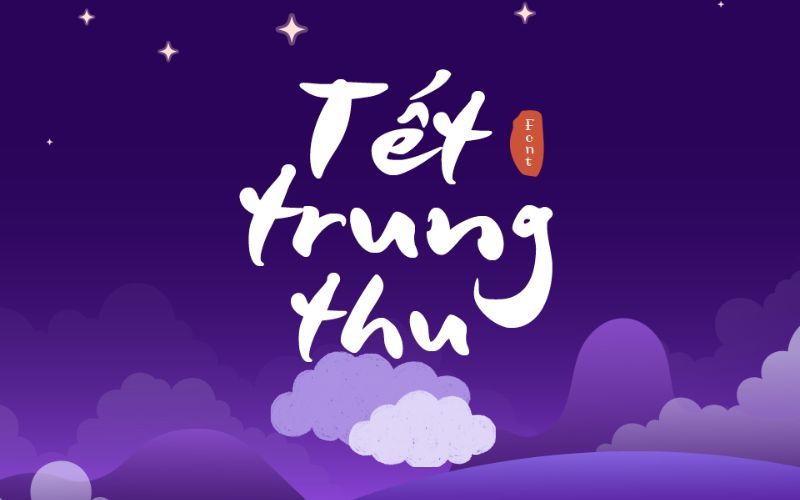
Trong thiết kế truyện tranh hay các sản phẩm sáng tạo như poster, video hoạt hình, font chữ đóng vai trò quan trọng trong việc thể hiện cảm xúc và phong cách riêng. Nếu bạn muốn mang đến sự sinh động, hài hước và cá tính cho tác phẩm, thì tải font chữ truyện tranh chính là lựa chọn hoàn hảo. Những bộ font chữ truyện tranh Việt hóa không chỉ giúp đoạn hội thoại trở nên tự nhiên, dễ đọc mà còn tăng tính thẩm mỹ cho toàn bộ thiết kế. Cùng Vietkey khám phá ngay các font truyện tranh đẹp và cách tải nhanh chóng trong bài viết dưới đây.
Giới thiệu chung về font chữ truyện tranh
Font chữ truyện tranh là kiểu chữ được thiết kế riêng để thể hiện cảm xúc, hành động và lời thoại trong các tác phẩm manga, comic hay truyện tranh minh họa. Khác với font chữ thông thường, font truyện tranh có đường nét sinh động, mềm mại hoặc phá cách, giúp người đọc cảm nhận được cảm xúc nhân vật một cách trực quan hơn.
Không chỉ giới hạn trong truyện tranh, những font chữ truyện tranh Việt hóa ngày nay còn được ứng dụng rộng rãi trong thiết kế poster, banner, video hoạt hình, hay các ấn phẩm sáng tạo dành cho trẻ em. Nhờ sự đa dạng về phong cách – từ dễ thương, vui nhộn đến mạnh mẽ, hành động – các font này giúp nhà thiết kế tự do thể hiện cá tính và phong cách riêng trong từng dự án.
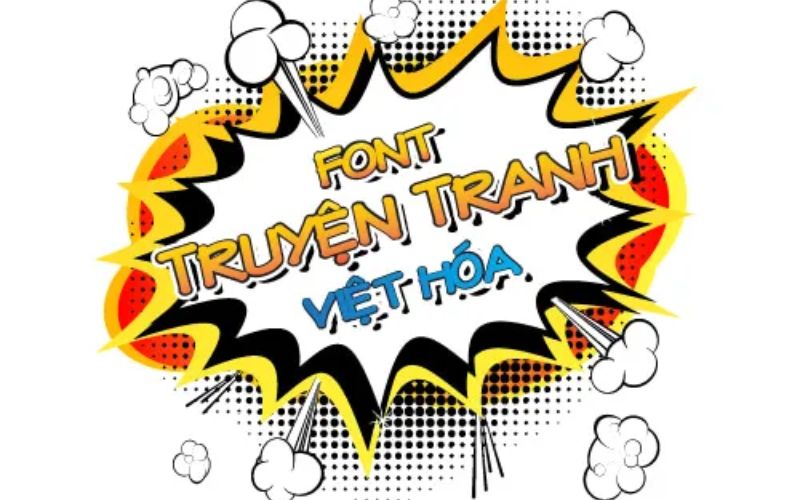
Vì sao nên dùng font chữ truyện tranh?
Việc sử dụng font chữ truyện tranh không chỉ giúp tác phẩm trở nên sinh động hơn mà còn góp phần truyền tải cảm xúc và câu chuyện một cách rõ nét hơn. Mỗi kiểu font đều mang một sắc thái riêng — có loại tươi vui, dễ thương phù hợp với truyện thiếu nhi, có loại mạnh mẽ, góc cạnh dành cho truyện hành động hay phiêu lưu.
Ngoài ra, font truyện tranh Việt hóa còn giúp người sáng tạo dễ dàng Việt hóa nội dung mà vẫn giữ được phong cách đặc trưng của truyện tranh Nhật Bản hay Âu Mỹ. Với các nhà thiết kế, việc chọn đúng font sẽ giúp bố cục hài hòa, thu hút ánh nhìn và tạo dấu ấn riêng cho sản phẩm. Vì thế, sử dụng font truyện tranh là yếu tố không thể thiếu để nâng cao chất lượng hình ảnh và trải nghiệm thị giác của người đọc.
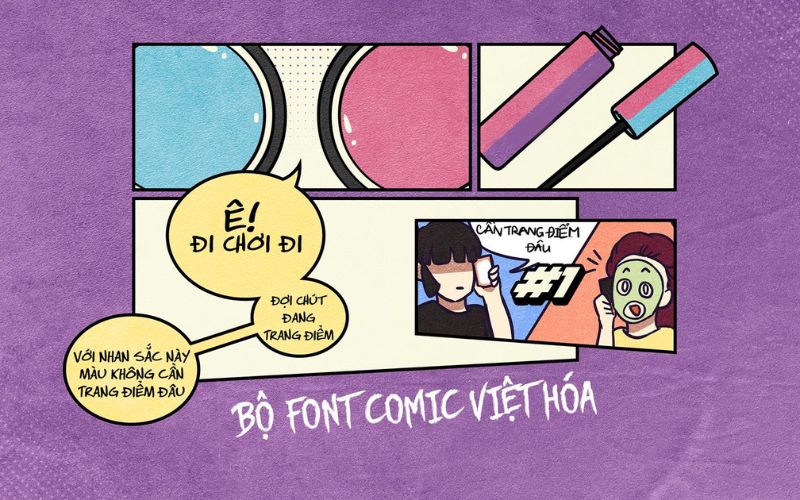
Các font chữ truyện tranh đẹp và dễ dùng nhất hiện nay
Nếu bạn đang tìm kiếm những kiểu chữ sinh động, đậm chất comic để làm nổi bật tác phẩm của mình, thì các font chữ truyện tranh đẹp và dễ dùng nhất hiện nay dưới đây chắc chắn sẽ là lựa chọn hoàn hảo.
Font Teddy Bear
Font Teddy Bear mang phong cách ngộ nghĩnh, đáng yêu, thường được sử dụng trong truyện tranh dành cho thiếu nhi hoặc các thiết kế vui nhộn. Các nét chữ tròn trịa, mềm mại tạo cảm giác thân thiện và dễ đọc. Khi tải font chữ truyện tranh Teddy Bear, bạn có thể áp dụng cho tiêu đề truyện, tranh minh họa hoặc poster hoạt hình. Đây là lựa chọn hoàn hảo cho những ai muốn mang lại cảm xúc nhẹ nhàng, vui tươi trong thiết kế mà vẫn giữ được sự chuyên nghiệp và thẩm mỹ cao.
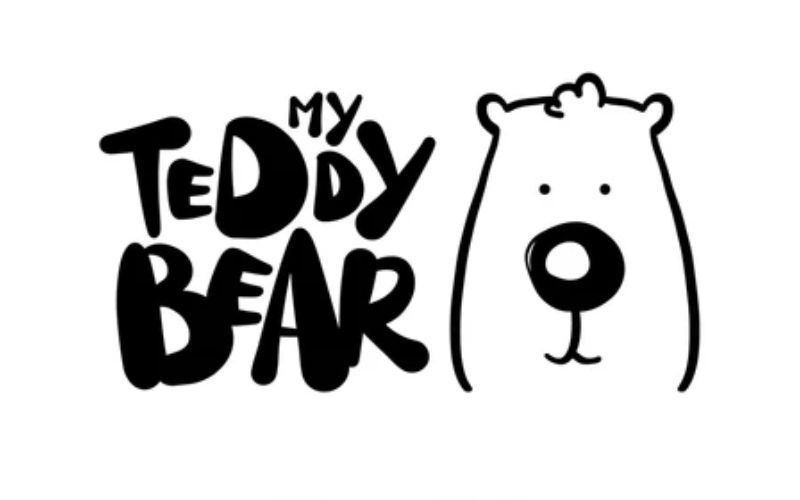
Font Anime Ace 3 Việt hóa
Anime Ace 3 Việt hóa là một trong những font truyện tranh phổ biến nhất hiện nay, đặc biệt được ưa chuộng trong các bản truyện Việt hóa. Font có thiết kế rõ ràng, đậm nét và phù hợp cho phần thoại, lời kể hoặc hiệu ứng âm thanh trong manga. Khi tải font chữ truyện tranh Anime Ace 3 Việt hóa, bạn sẽ có được kiểu chữ mang phong cách Nhật Bản đặc trưng, vừa hiện đại vừa dễ đọc. Đây là lựa chọn lý tưởng cho các nhóm dịch truyện, họa sĩ hoặc nhà thiết kế yêu thích phong cách comic – anime.
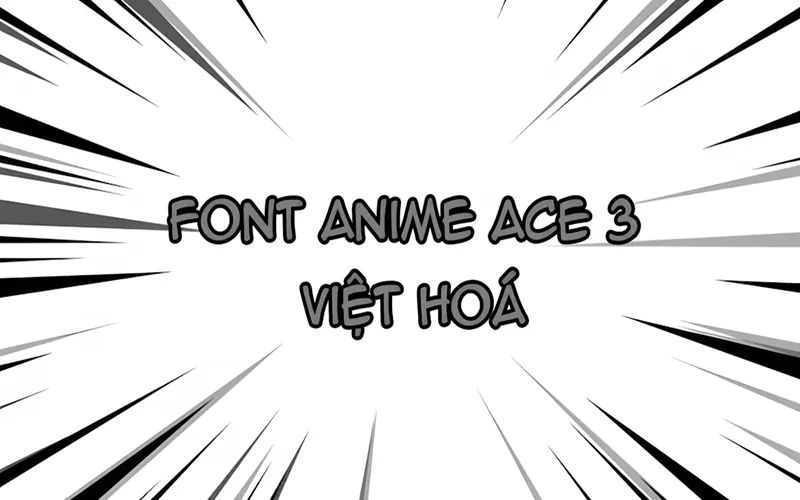
Font HL Comic
Font HL Comic nổi bật với kiểu chữ dày, chắc và có độ tương phản cao giữa các nét, mang lại cảm giác mạnh mẽ và sinh động. Font này thường được sử dụng trong truyện tranh hành động hoặc các thiết kế cần sự nổi bật về thị giác. Khi tải font chữ truyện tranh HL Comic, bạn có thể dùng để thiết kế tiêu đề, hiệu ứng “boom”, “bang” hoặc lời thoại nhân vật. Với khả năng hiển thị tốt cả trên màn hình và in ấn, HL Comic là lựa chọn hoàn hảo cho các nhà sáng tạo nội dung truyện tranh chuyên nghiệp.
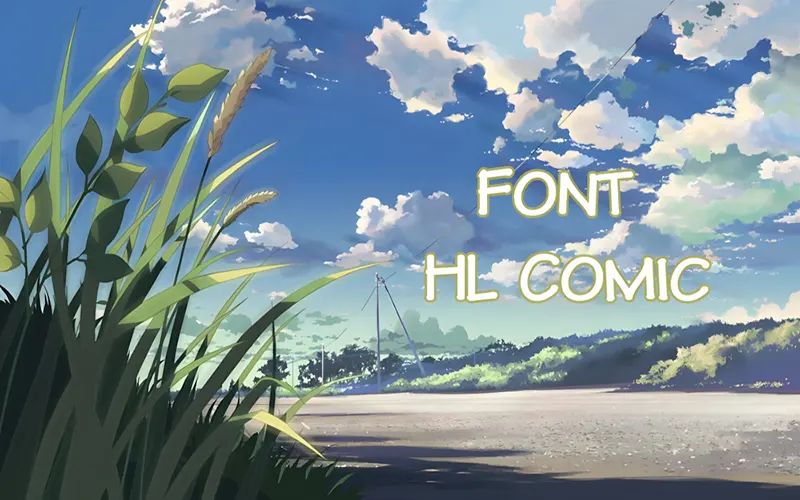
Font MTO
Font MTO được thiết kế với phong cách comic cổ điển, tái hiện tinh thần của những tạp chí truyện tranh thập niên 80 – 90. Các nét chữ mềm nhưng mạnh, dễ đọc và cân đối, phù hợp với nhiều thể loại từ hành động, phiêu lưu đến lãng mạn. Khi tải font chữ truyện tranh MTO, bạn sẽ thấy font này hoạt động tốt cả trong phần thoại và tiêu đề, mang đến cảm giác hoài cổ nhưng vẫn hiện đại. Đây là font chữ được nhiều designer và nhóm dịch truyện sử dụng vì tính linh hoạt và khả năng tương thích cao.
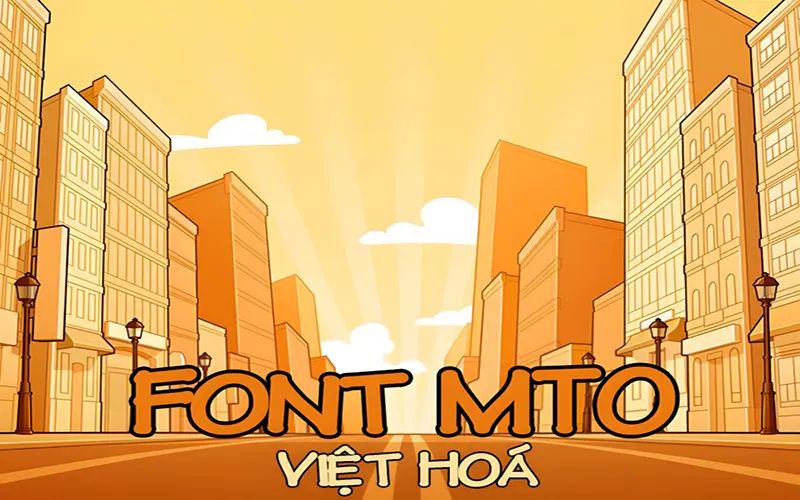
Spider Man Font
Spider Man Font được lấy cảm hứng từ phong cách chữ trong series truyện tranh nổi tiếng cùng tên của Marvel. Các nét chữ góc cạnh, đậm và mang hơi hướng siêu anh hùng giúp font trở nên nổi bật và cuốn hút. Khi tải font chữ truyện tranh Spider Man, bạn có thể sử dụng trong các thiết kế poster, tiêu đề hoặc bìa truyện để tạo cảm giác hành động và kịch tính. Đây là font đặc biệt dành cho những ai yêu thích dòng truyện siêu anh hùng và muốn thể hiện năng lượng mạnh mẽ trong sản phẩm thiết kế của mình.
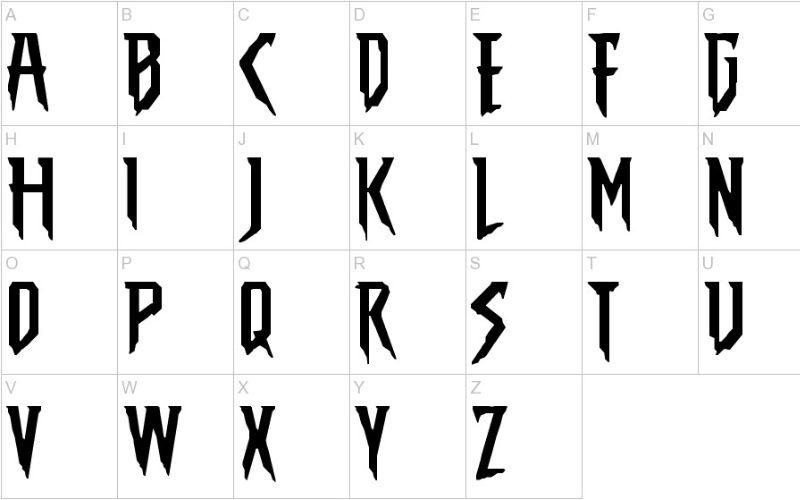
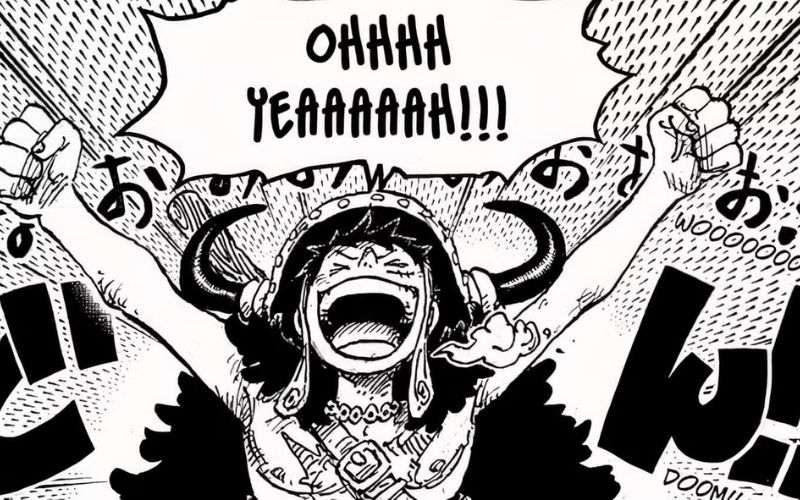
Trên đây là tổng hợp những font chữ truyện tranh đẹp và dễ dùng nhất cùng các mẹo giúp bạn sử dụng hiệu quả trong thiết kế. Việc lựa chọn đúng font không chỉ giúp tác phẩm của bạn trở nên sống động, cuốn hút mà còn thể hiện rõ cá tính và cảm xúc của nhân vật. Dù bạn là người vẽ truyện, designer hay chỉ muốn tạo poster phong cách comic, hãy tải font chữ truyện tranh phù hợp để nâng tầm chất lượng sáng tạo của mình. Đừng quên thử nghiệm nhiều kiểu chữ khác nhau để tìm ra phong cách riêng cho dự án của bạn nhé!